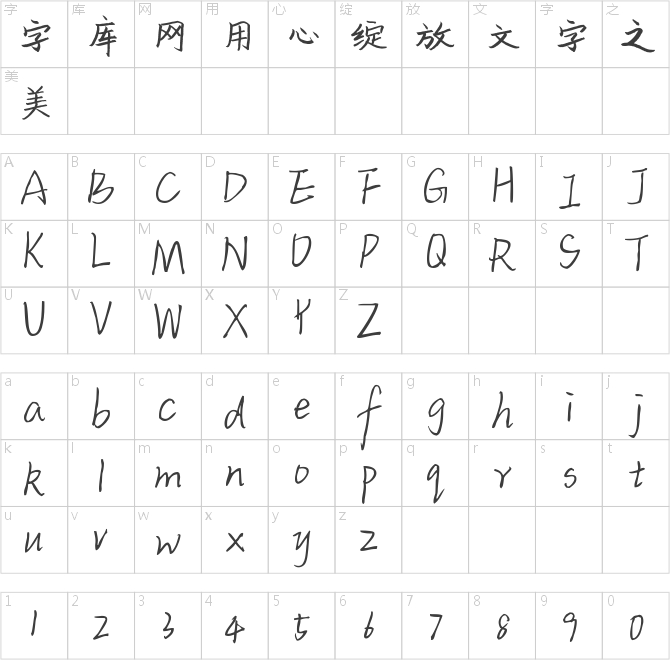
字樂(lè)海風(fēng)明信片
字樂(lè)海風(fēng)明信片字體字庫(kù)是一款讓人賞心悅目、百看不厭的中文字體,適合各類廣告和產(chǎn)品包裝設(shè)計(jì)應(yīng)用,字體大小16.34MB,格式為ttf字體,上傳用戶是神經(jīng)蛙6,作者/版權(quán)方為字體圈